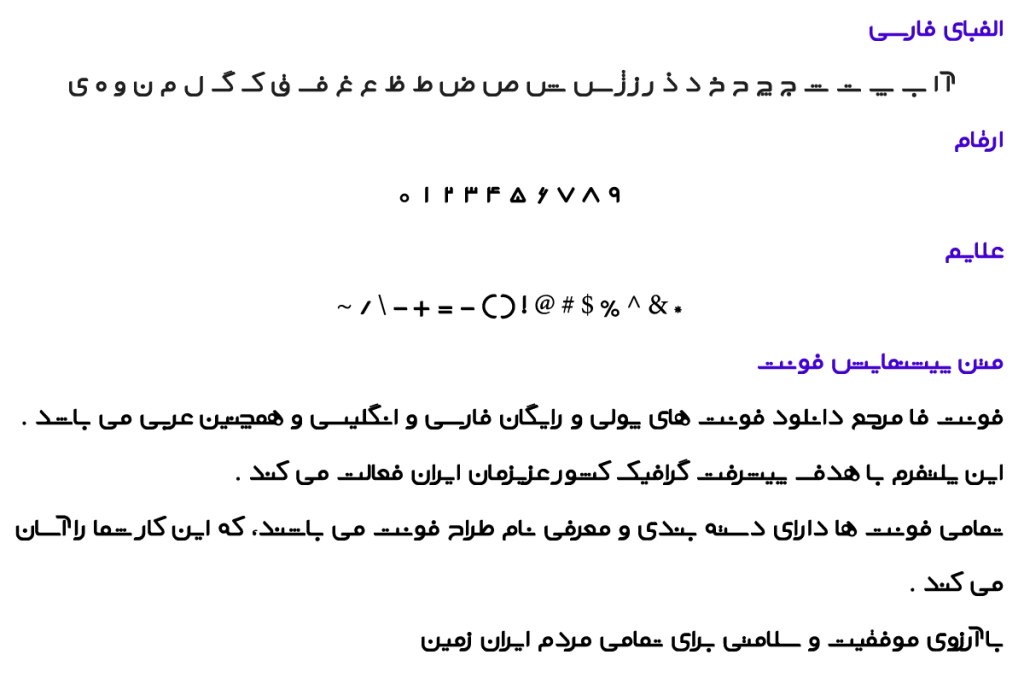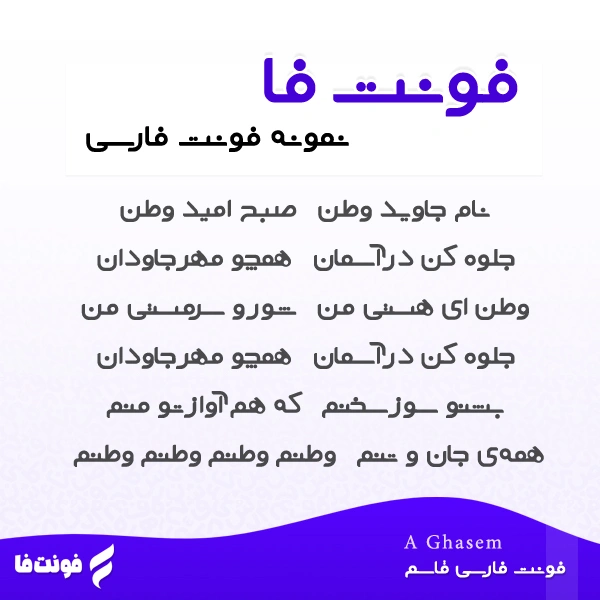
فونت فارسی قاسم – A Ghasem
سال ساخت فونت: 1393
طراح فونت: قاسم نجاری نوع فونت: فونت هندسی
پیشنمایش فونت قاسم
توضیحات و معرفی فونت قاسم
فونت فارسی قاسم ( A Ghasem ) از مجموعه فونت های آزاد می باشد، و نیز نوع فونت هندسی می باشد.
فونت خوشگل مربوط توسط قاسم نجاری در سال 1393 براساس فونت یکان طراحی و ساخته شده است.
و نیز فونت A Ghasem در یک وزن پر رنگ است.
در تصویر زیر میتوانید شعر دلنشین «نام جاوید وطن» را ببینید که با این تایپ فیس فارسی طراحی شده است.